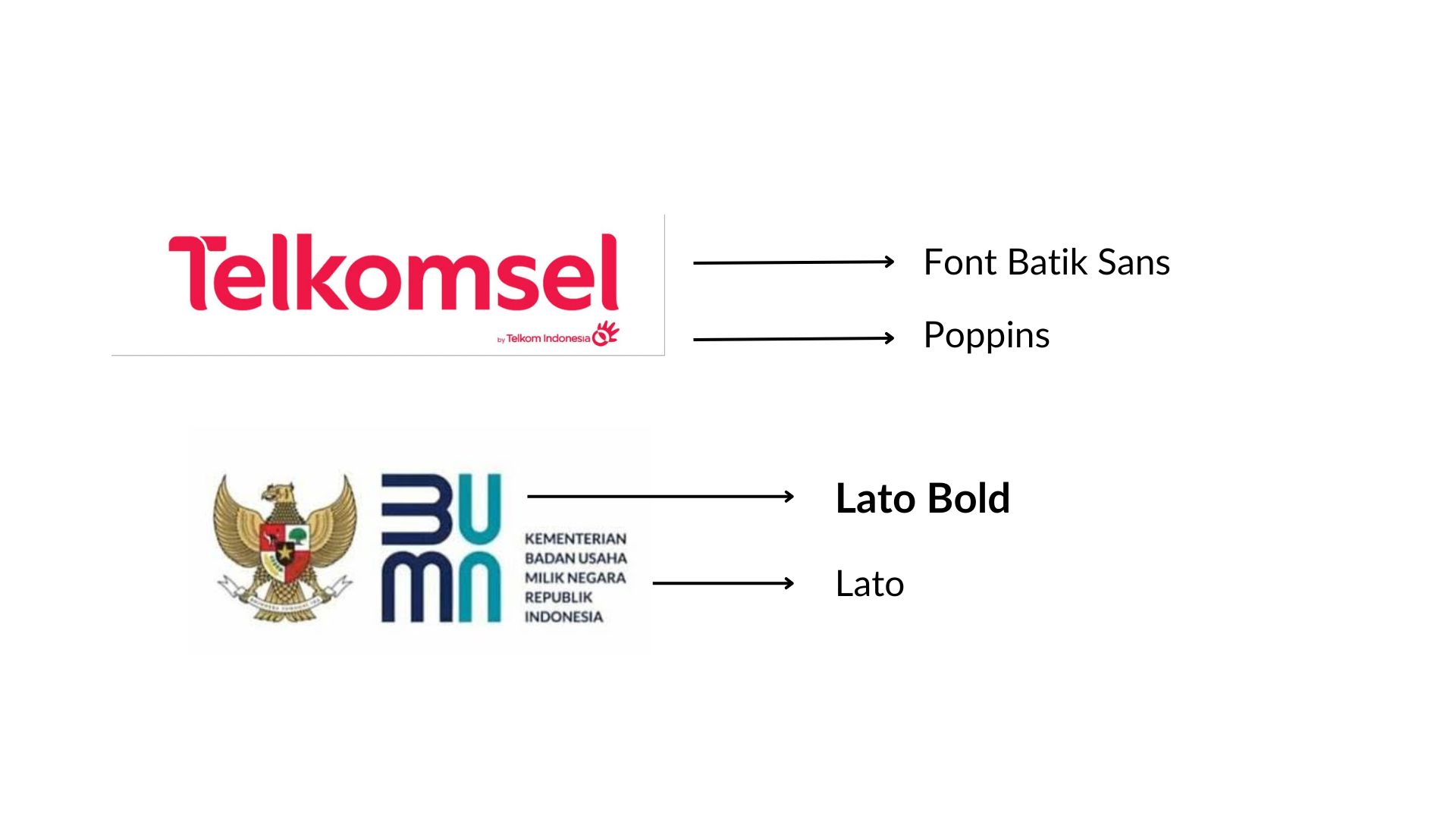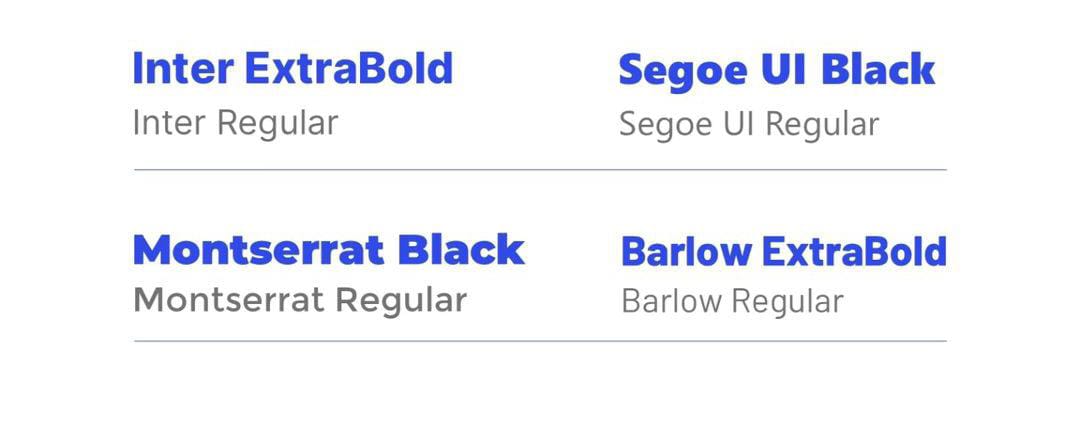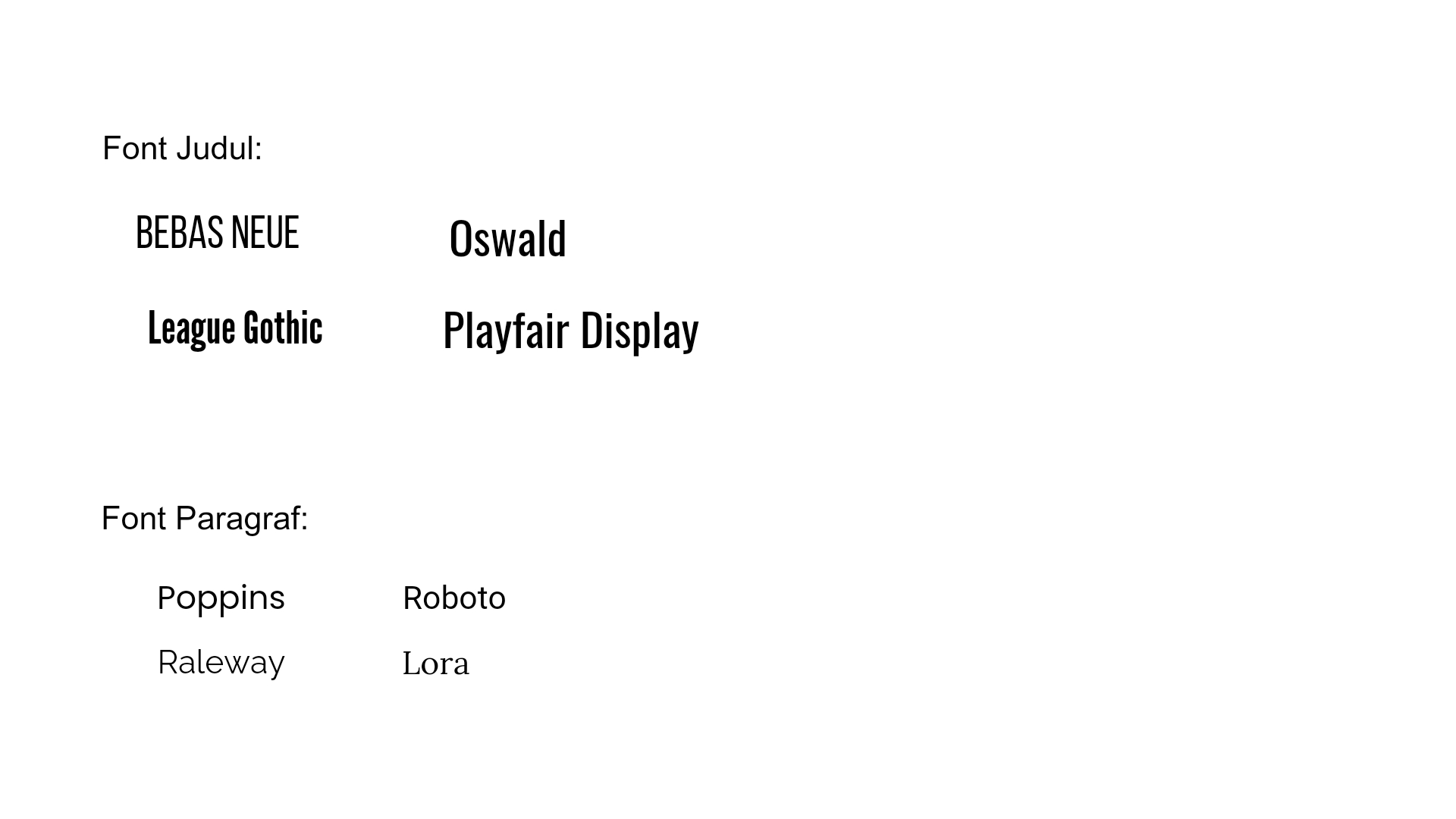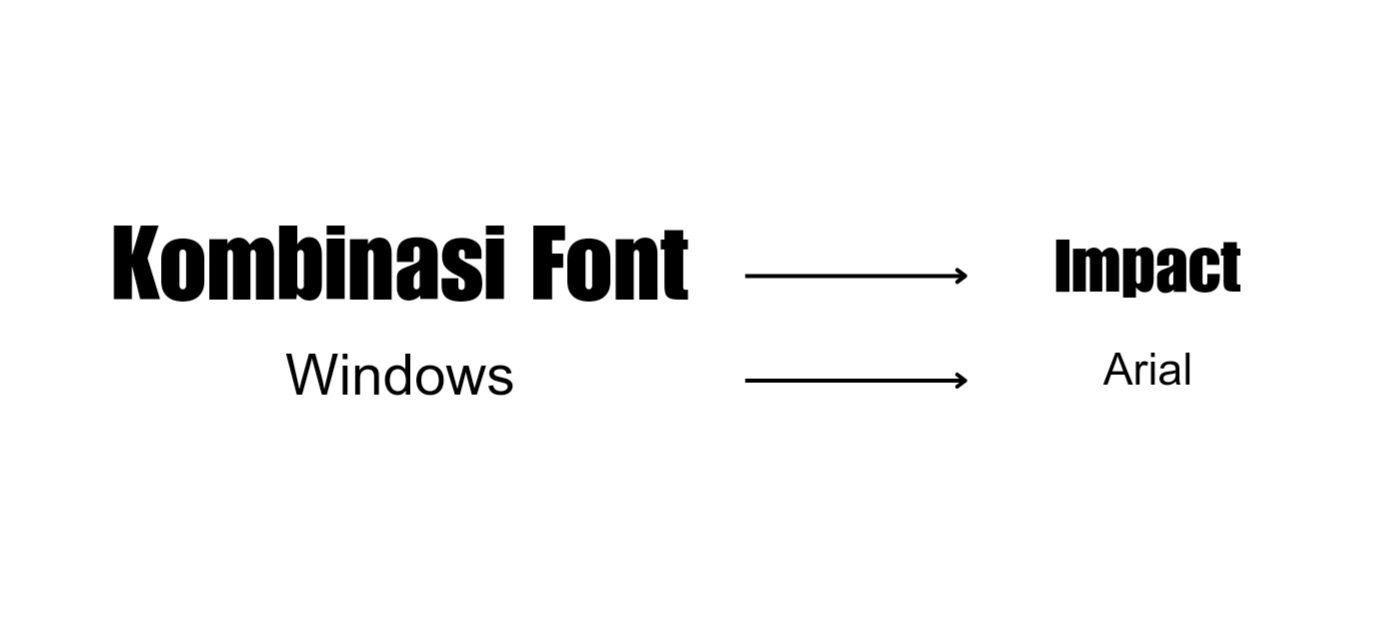
Tips Kombinasi Font Desain Konten dan Branding yang Keren
Dalam desain grafis kombinasi font dapat dibuat dengan bervariasi agar teks tidak membosankan sehingga desain konten dan brandin lebih menarik. Ketika desain grafis digunakan untuk konten dan branding yang bisanya memiliki beberapa teks, font perlu dikombinasikan agar menarik. Tips penting dalam memilih kombinasi font untuk desain konten dan branding adalah perbedaan jenis font, style huruf hingga ukuran teks.
Kombinasi dua atau tiga font dalam desain memiliki aturan tersendiri agar harmonis dan berguna menciptakan hirarki visual. Jumlah font yang digunakan harus menyesuaikan kebutuhan teks dan tidak boleh terlalu banyak. Perhatikan penggunaan font agar dapat mengkombinasikan dengan harmonis dan relevan, karena untuk branding dan desain konten perlu sesuai identitas merek.
TIPS KOMBINASI FONT DESAIN KONTEN DAN BRANDING
Ketika menciptakan desain visual yang menarik, kombinasi font yang dipilih berperan penting agar teks mudah dibaca dan menarik perhatian. Desain konten mengkombinasikan font untuk menciptakan hirarki dan urutan pembacan yang jelas. Dalam branding kombinasi font yang berbeda akan menciptakan kontras yang menarik. Berikut beberapa tips memilih kombinasi font untuk desain konten branding yang keren:
Dalam desain branding kombinasi font berguna merepresentasikan identitas merek dengan baik. Biasanya menggunakan dua atau tiga font untuk digunakan sebagai brand guideline. Dalam brand guideline ini font yang dipilih akan digunakan dalam semua jenis desain brand dengan konsisten.
Sebuah brand atau perusahaan akan memiliki brand guideline yang berisi berbagai elemen visual termasuk font yang digunakan oleh brand. Elemen branding dalam brand guideline biasanya terdiri dari:
• Palet Warna
• Elemen Grafis
• Shapes Geometris
• Gambar
• Dua atau Tiga Font yang Harmonis
Agar lebih fleksibel brand guideline sering menggunakan dua font atau lebih yang merepresentasikan karakter dan identitas merek. Contohnya kombinasi dua font berbeda pada desain logo telkomsel yang menggunakan font batik sans dan poppins. Font logo BUMN juga mengkombinasikan dua gaya huruf dalam satu typeface yaitu Lato bold dan Lato.
Kombinasi Font Windows
Saat menciptakan desain di komputer atau laptop gunakan kombinasi font untuk desain konten branding menggunakan font default. Kombinasi font yang mengambil dari situs tertentu belum tentu gratis dan bisa ada masalah lisensi. Mengkombinasikan font yang sudah ada di windows tidak perlu repot melakukan install.
Font bawaan windows yang tidak kalah keren dengan font dari berbagai situs font adalah seperti impact atau georgia. Ciptakan kontras font dengan menciptakan kombinasi dua font yang memiliki ketebalan huruf berbeda. Contoh kombinasi font windows yang keren seperti Impact dan Arial, atau kombinasi Tahoma dan Verdana, Kombinasi sesama sans serif dengan ketebalan berbeda akan kontras.
Kombinasikan Font dalam Family yang Sama
Dalam desain konten dan branding kombinasi font tidak boleh terlalu berbeda atau tidak harmonis karena keterbacaan teks perlu diutamakan juga. Pada desain branding kombinasi font harus harmonis dan mirip karena gaya font mencerminkan karakter merek atau identitas brand. Kombinasi font desain konten dan branding yang mirip dapat diciptakan dengan menggunakan font dalam jenis yang sama atau dalam family yang sama.
Contohnya kombinasi Inter Extrabold dan Inter Regular, perbedaan gaya huruf yang tebal dan regular menciptakan kontras yang cukup tetapi tetap harmonis. Perbedaan gaya huruf seperti ketebalan font atau gaya huruf italic dapat menciptakan kombinasi kontras dan harmonis.
Font judul atau teks utama akan menggunakan font tebal sementara font tipis akan digunakan untuk sub judul atau paragraf. Dalam desain branding, nama bisnis akan menggunakan font tebal sementara tagline akan menggunakan font tipis.
Bedakan Gaya Font Judul dan Font Paragraf
Desain grafis konten biasanya memiliki judul dan teks paragraf, yang mana perlu dibedakan gaya hurufnya agar mudah terbaca dan menciptakan hirarki visual. Kombinasi gaya yang berbeda akan membantu menonjolkan yang mana teks judul dan yang mana sub judul atau paragraf.
Perbedaan gaya huruf akan membantu dalam memudahkan audiens membaca informasi. Kombinasi font yang kontras dan berbeda untuk judul dan paragraf memiliki tujuan seperti:
• Menunjukkan tingkat kepentingan informasi
• Meningkatkan daya tarik visual
• Menciptakan Perbedaan Kontras antar Teks
Sementara font judul biasanya memiliki gaya huruf lebih tinggi dan tebal seperti font condensed, font paragraf memiliki gaya huruf pendek dan lebar, seringkali memiliki gaya huruf tipis. Beberapa font judul yang tebal dan menonjol seperti:
Kombinasi font dalam desain grafis yang digunakan untuk konten dan branding harus dipilih yang harmonis dan keren. Gaya font yang dikombinasikan untuk jenis desain yang sama bisa berbeda bergantung identitas merek dan tema desain. Pastikan untuk memilih font yang kontras, memiliki gaya huruf berbeda, ukuran berbeda dan digunakan pada jenis teks yang berbeda.